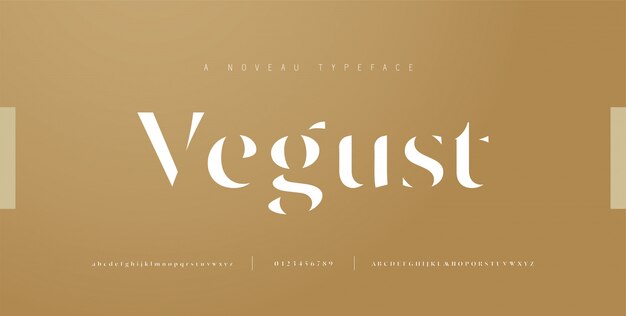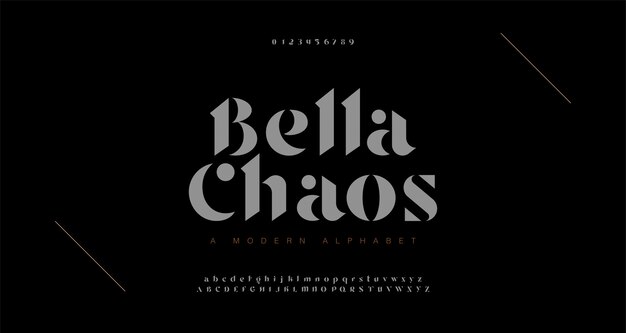
Font Numeri Eleganti
Font numeri eleganti. Scarica questo Vettore premium su Elegante alfabeto lettere serif font e set di numeri e scopri più di 11 milioni di risorse grafiche professionali su Freepik. La sezione "Generatore di testo" presenta semplici strumenti che ti permettono di creare grafiche con font di diversi stili così come vari effetti di testo;. Scarica questo Vettore premium su Elegante alfabeto lettere serif font e numero e scopri più di 10 milioni di risorse grafiche professionali su Freepik.
Inclusi in questo download vi sono un set di lettere, numeri, e punteggiatura per soddisfare i tuoi bisogni tipografici Kikuri Typeface Esplora il tuo lato creativo con questo unico font fatto a mano Questo font include elementi vettoriali al 100% che possono essere ridimensionati senza alcuna perdita di risoluzione. Scarica questo Vettore premium su Elegante alfabeto lettere serif font e numero caratteri tipografici classici maiuscoli, minuscoli e numeri regolari e scopri più di 10 milioni di risorse grafiche professionali su Freepik. Ideale per segnaletica, pubblicità o quant'altro è possibile per creare veloci lettere stile evidenziatore Jessica Forever Un carattere grazioso disegnato a mano Include uniche lettere maiuscole e minuscole, numeri e molti altri glifi.
I font Croce e delizia di ogni designer Le persone si approcciano in modo diverso ai font, c’è chi nemmeno sa che cosa sono o come sono fatti, ma c’è anche chi ne ha fatto un lavoroO addirittura un culto!. I font sono una parte fondamentale di un progetto grafico devono veicolare informazioni, essere chiari, leggibili La scelta di un font ben progettato, coerente e bello è indice di professionalità, competenza e cura del progetto Nel grande mare di font disponibili sul web, ce ne sono alcuni che è possibile scaricare gratuitamente. Font e Dingbat Gratis L'obiettivo di FontRivercom è fornire ai nostri visitatori i migliori font, dingbats e barre di font per PC e Mac La nostra offerta include contenuti completi, ricerca veloce di font e una ottima selezione di caratteri di stampa originali e famiglie di font organizzate per categoria.
La sezione "Raccolta font" è il posto dove puoi vedere l'anteprima e scaricare font gratuiti. I font moderni sono affilati, eleganti, audaci, professionali ed eleganti numeri e punteggiatura Se i font moderni sono proprio quello di cui il tuo sito web WordPress ha bisogno 📝, dai un'occhiata a questa guida con più di 50 frizzanti soluzioni. Questo font Serif ha un’aria femminile e sbarazzina Elsie presenta elementi del font Bodoni, con grazie arricciate che aggiungono un tocco di personalità in più senza distrarre troppo dal contenuto È disponibile nella versione regolare, con lettere maiuscole swash (lettere maiuscole con uno stile più particolare), grassetto pesante, e con leggere maiuscole swash in grassetto pesante.
Download the Aerovias Brasil font by Nicks Fonts The Aerovias Brasil font has been downloaded 143,534 times. Quando si parla di font per l’architettura, esistono due categorie di persone La prima è costituita da tutti quelli che impiegano più tempo a scegliere il font per le tavole, o addirittura il font per il portfolio, che ad impaginarli!. In un mare infinito di caratteri è normale perdersi e navigare ore e ore attraverso le forme più varie, aggraziate o bastoni (meglio conosciuti come serif e sans serif), che all’improvviso sembrano diventare tutte uguali, ma che in realtà nascondono insidiosi dettagliGli uomini hanno sempre avuto i loro “caratteri”, – e.